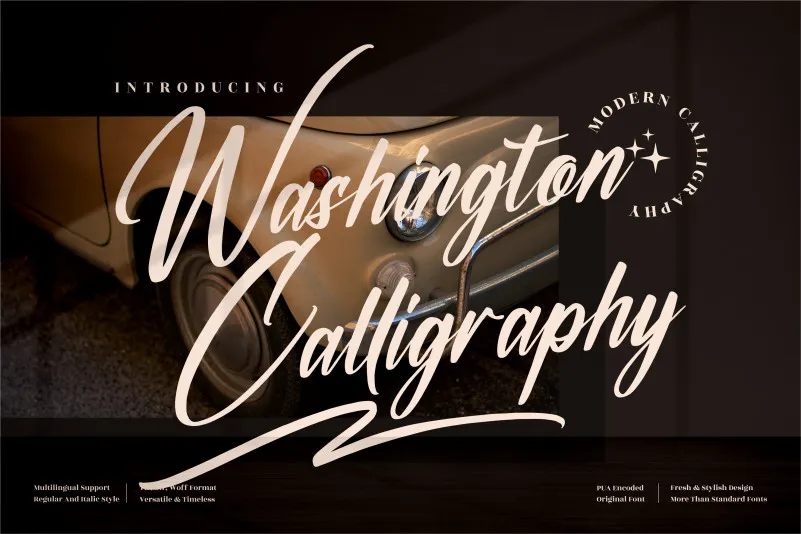
Esta é uma fonte de escrita com efeito que foi cuidadosamente criada para adicionar um toque elegante à sua composição de texto. Seja para personalizar suas postagens no Instagram ou criar scripts para projetos DIY, essa fonte transformará qualquer ideia criativa em verdadeiros trabalhos de arte! Esta fonte é PUA codificada, o que significa que você pode acessar todos os caracteres e ondas com facilidade. Washington Font é perfeito tanto para aqueles que buscam um toque de mágica em suas composições quanto para designers aficionados por escrita a mão. Este poderoso conjunto de fontes oferece uma ampla gama de opções, criando diferentes efeitos dependendo do uso. Engane-se se pensasse que é apenas uma fonte; Washington Font se transforma no seu favorito pelo seu poder de personalização.